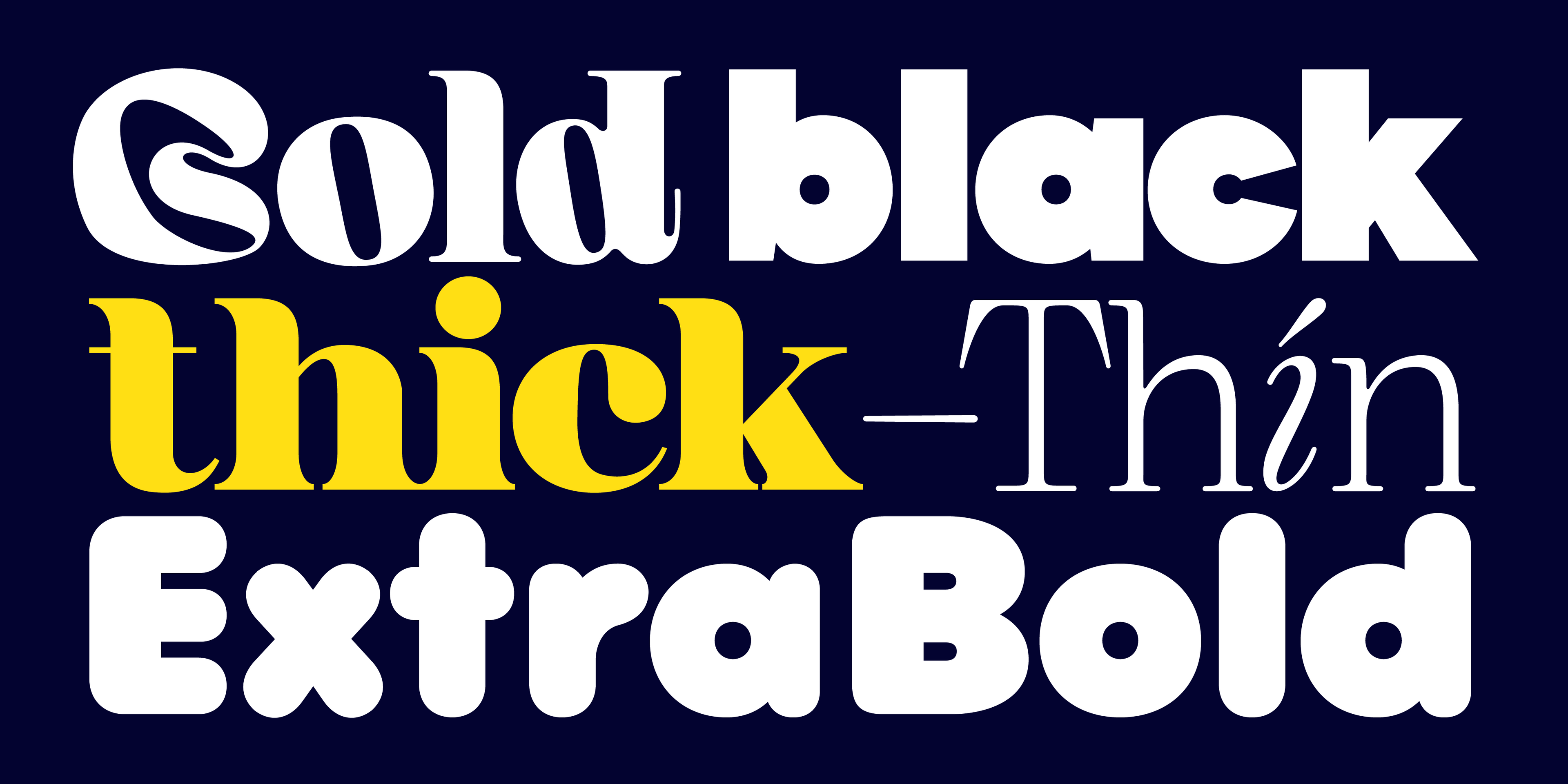
Las fuentes gruesas suelen denominarse "fuentes en negrita" o "fuentes pesadas" debido a su mayor grosor, también conocido como la negrita de los trazos de las letras. Desde una perspectiva técnica, los grosores de las fuentes varían de 100 a 900, a menudo en pasos de cien. Cada paso corresponde a un nombre de grosor; por ejemplo, 400 suele ser igual a Regular.
Aquí se muestraKijs Thin y SemiBold.
Una distribución de pesos de fuentes popular es la siguiente: 100 = Thin, 200 = ExtraLight, 300 = Light, 400 = Regular, 500 = Medium, 600 = SemiBold, 700 = Bold, 800 = ExtraBold y 900 = Black. Sin embargo, los diseñadores tipográficos pueden establecer sus números en el proceso de diseño según el aspecto que quieran lograr.
¿Qué son las fuentes en negrita?
Los grosores de fuente Bold, ExtraBold y Black suelen considerarse fuentes "gruesas". Las fuentes suelen venir como familias de fuentes, lo que significa que tienen múltiples grosores dentro de un estilo de familia. Regular y Bold suelen estar incluidos cuando compras una familia de fuentes básica, pero una familia de fuentes profesional puede tener hasta nueve grosores de fuente además de sus grosores de cursiva correspondientes.
Al elegir una fuente y su grosor para un proyecto de diseño, tenga en cuenta que las fuentes en negrita suelen dar una impresión más juvenil, más llamativa y más accesible. Por el contrario, las fuentes más livianas tienen un aspecto más elegante y refinado.
Fuentes gruesas y redondeadas de alto contraste
Bauhaus Soft ExtraBold (800) es una fuente serif redondeada que viene en grosores finos y gruesos, desde 100 hasta 900. Soft es una tipografía moderna de alto contraste con un estilo orgánico: se vuelve más fluida cuanto mayor es el grosor de la fuente. Las esquinas superiores derechas del tallo están redondeadas, lo que le da a la tipografía un aspecto suave y cálido.
Bauhaus Chez Bold (700) es una tipografía sans serif de alto contraste . Esta fuente también viene en nueve grosores, incluidos los estilos fino y muy atrevido. Las esquinas superiores de los apéndices de las letras y los extremos de las bolas son pronunciados y redondeados. Chez es una tipografía sans serif moderna y agradable, perfecta para marcas de alimentos y belleza.
Bauhaus Goji es una tipografía agradable y redondeada con un tacto de tinta. Cuanto más audaz sea el peso, más suave será el diseño. La marca Crocs utiliza una fuente similar para su logotipo denominativo para demostrar comodidad; la marca está escrita en minúsculas para enfatizar la naturaleza social de la marca.
Fuentes modernas y gruesas
Bauhaus Bool es una tipografía moderna y divertida , ideal para la creación de marcas, ya que incluye muchos diseños de letras alternativos, por ejemplo, la letra B (ver imagen). Las letras modernas son obras de arte y ayudan a los diseñadores gráficos a hacer que su trabajo se destaque.
Bauhaus Rail en ExtraBold (800) es una fuente sans-serif divertida y moderna que lleva la idea de una fuente de alto contraste en una dirección diferente y muestra, por ejemplo, barras horizontales como cadenas.
Fuentes escritas a mano con grosores en negrita
Skay es una fuente de burbuja manuscrita que funciona mejor en sus grosores más gruesos. La fuente solo tiene letras mayúsculas, lo que la hace ideal para el diseño de logotipos y tipos de letra de exhibición. El carácter de Skay es orgánico, fluido y flexible.
Lace Rounded es una versión redondeada de la fuente Lace, lo que la hace un poco más accesible y amigable. Tanto Lace como Lace Rounded tienen un estilo de escritura a mano con líneas monolineales y tienen nueve grosores de fuente cada una.